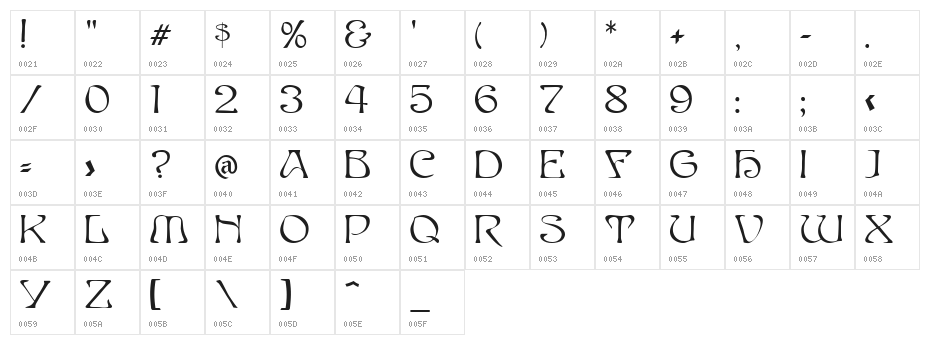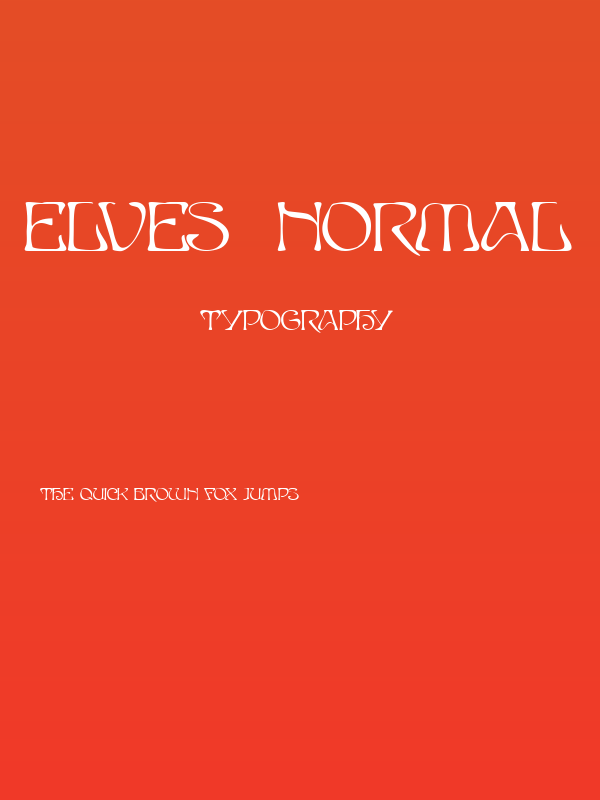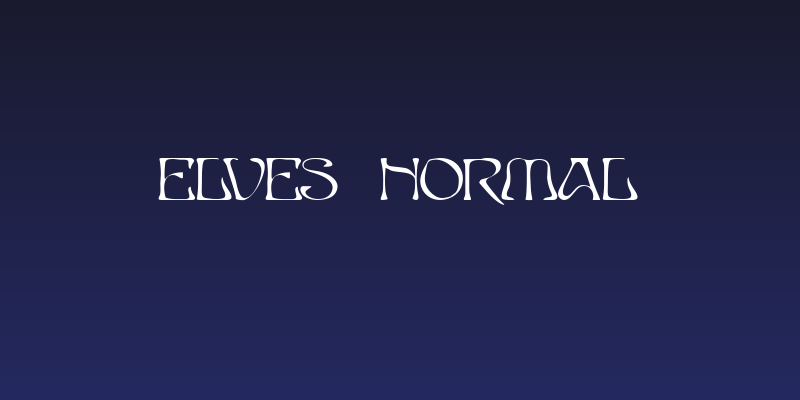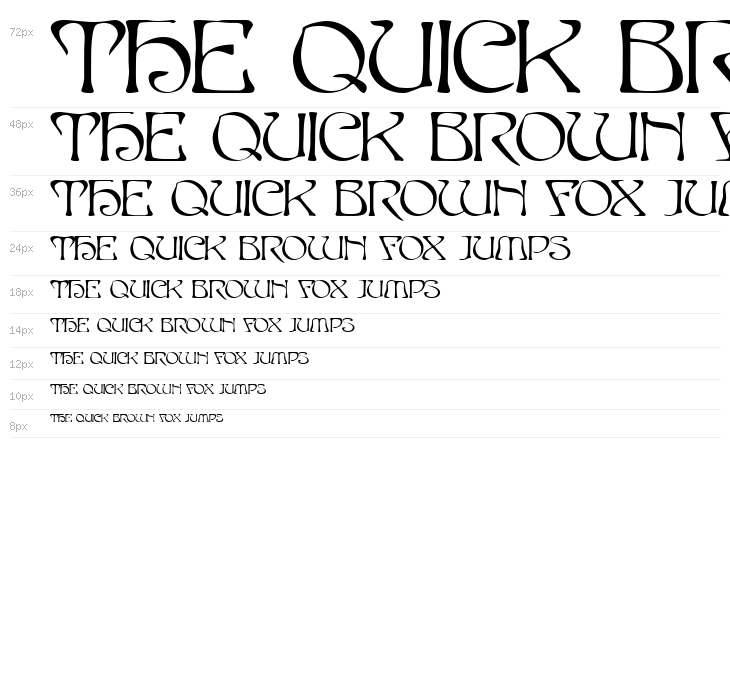
Elves Normal Font
✎ Script
| 整体风格 | Whimsical, Artistic |
| 使用场景 | Headlines, Logos, Creative projects |
| 推荐项目 | Ideal for fantasy-themed projects, artistic branding, event invitations, and creative book covers. |